「にじみ・墨だまり」におすすめの日本語フリーフォント
今回は、文字を構成する線が交わるところにインクのにじみや・墨が溜まっているような質感になっている「墨だまり(墨溜まり)」があるおすすめの日本語フリーフォントをまとめてみました。
数年前からモリサワの「A1明朝」「A1ゴシック」フォントといった「墨だまり」加工されたフォントがトレンドになり、広告などに取り入れらているのを多く見かけるようになってきました。
フリーフォントでもそのような「墨だまり(墨溜まり)」表現されているフォントがあるので、ご紹介します。
「にじみ・墨だまり」の日本語フリーフォント
一般的な文字と墨だまり加工された文字を比較してみると違いがよくわかります。
本記事では、このような墨だまり表現されているフォントをご紹介します。
モボ
つなぎゴシック
つなぎゴシックフォントは、インパクトのある極太ウェイト、角丸加工が加えられていることで柔らかな印象があります。ひらがな・カタカナがこぶりに作られているので、柔らかく優しい雰囲気もあります。
モリサワの「A1ゴシック」のようなウェイトと墨だまりの質感が似ています。
築豊35ポイントゴチック
築豊35ポイントゴチックフォントは、ゴシック体ながら明朝体のようなハネハライの筆脈と筆勢付いているたオールド系のゴシック体フォントです。
ひぐれゴシック
ひぐれゴシックは、漢字の文字が墨だまりが強めにかかっているのがステキなゴシック体フォントです。
しっぽり太ゴチック
しっぽり太ゴチックは、レトロで古風な印象をもつ、伝統的なスタイルの太ゴシック体です。
オールドスタイルの文字に加えて、墨だまり加工が古風で味がある顔を見てくれるフォントです。
ひな明朝
ひな明朝フォントは、全体的に丸みを帯びており、漢字は細めにデザインされているため、『品格さ』を感じさせてくれる明朝体フォントです。
はれのそら明朝
はれのそら明朝フォントは、少なめの墨だまり加工を施されていて、角丸ですっきりとした明朝体フォントです。上品さが表現されているステキなフォントです。
ニューテゴミン
ニューテゴミン(New Tegomin)フォントは、文字の輪郭にしっかりとしたインクのにじみが表現されていることで、レトロさと柔らかい雰囲気の表情をもつオールドスタイル明朝体で手書き+明朝体のようなフォントです。
さつき源代明朝
さつき源代明朝フォントは、しっかりとした太さをもち、墨だまりが施されていることで温かみのある印象を作り出しています。
紙モノゴシック
紙モノゴシックフォントは、紙面での使用を目的に設計している見出し用ゴシック体フォントです。ややぽってりとした印象が、柔らかさと可愛さを兼ね備えているデザインゴシック体です。
装甲明朝
装甲明朝フォントは、横線が極細で、切込みが入ったステンシル体風の見出し向け明朝体フォントです。切り込みと墨だまりの2つの加工が施されていることで、他にはない味があるデザインフォントとなっています。
Oradano明朝
Oradano明朝フォントは、「活字の格好よさの源泉を考える材料」をテーマに、東京築地活版製造所が明治30年に販売していたフォントをベースに作られたフォントです。
インクのにじみが強めに表現されているかっこいいフォントです。
XANO明朝フォント
XANO明朝フォントは、活版印刷時代の活字のような味わいとレトロさがあるヴィンテージ風な明朝体フォントです。
雨墨ゴシック
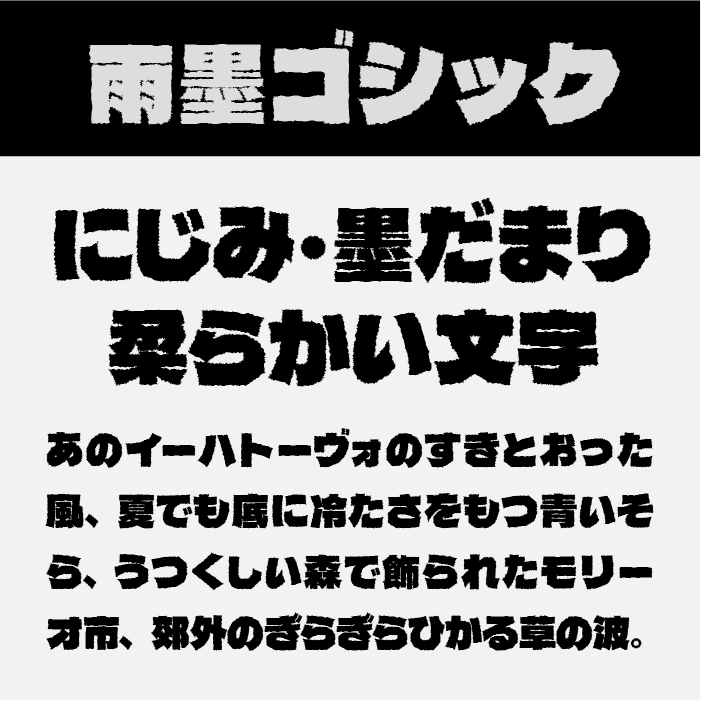
雨墨ゴシックフォントは、極太ゴシックで直線的なゴシック体に、あえて滲みやかすれ、ラフっぽい質感を重なっていることで、冷たさと温かさがミックスされた不思議な雰囲気を感じるデザインです。